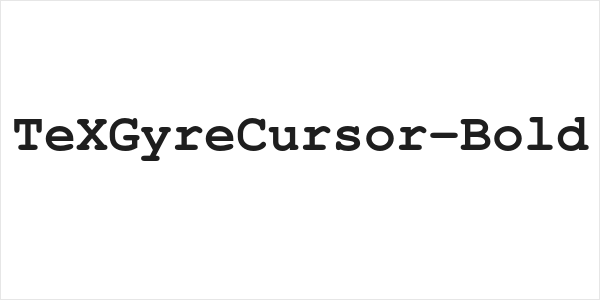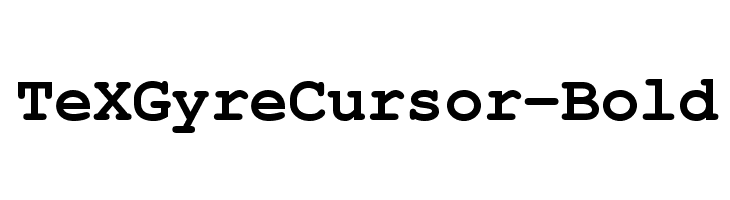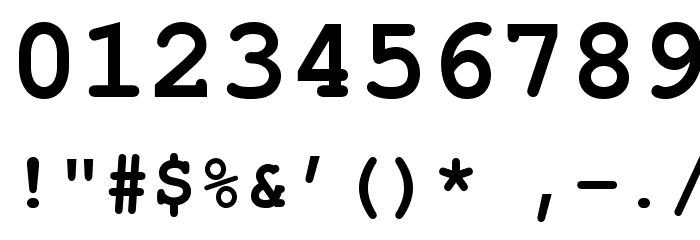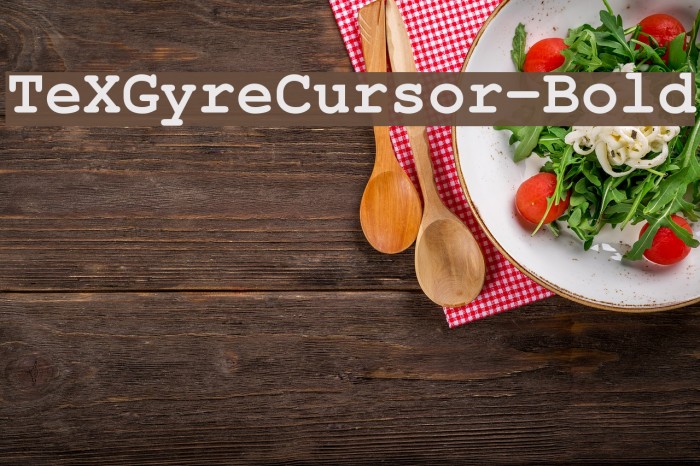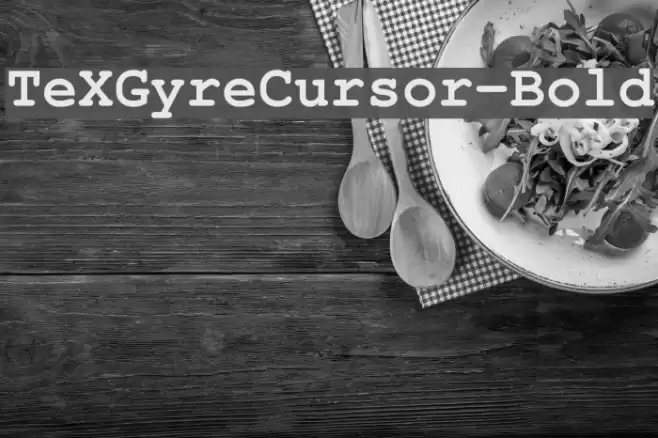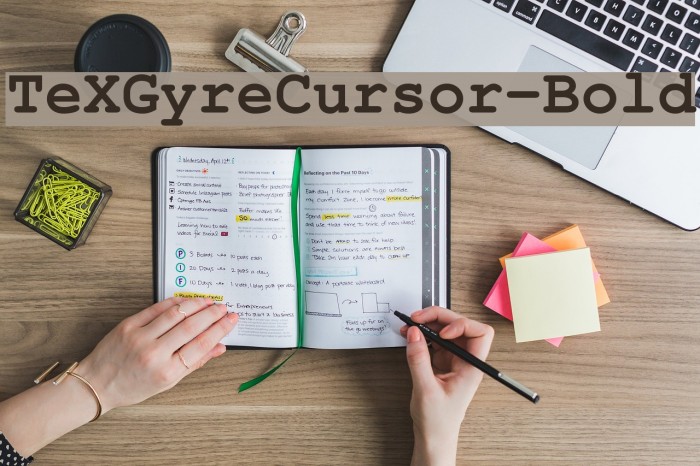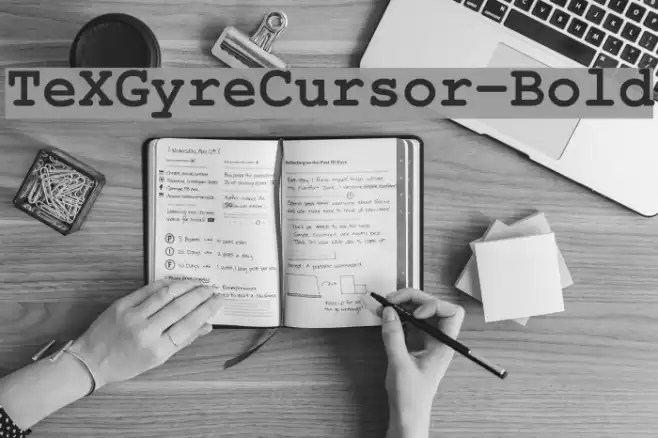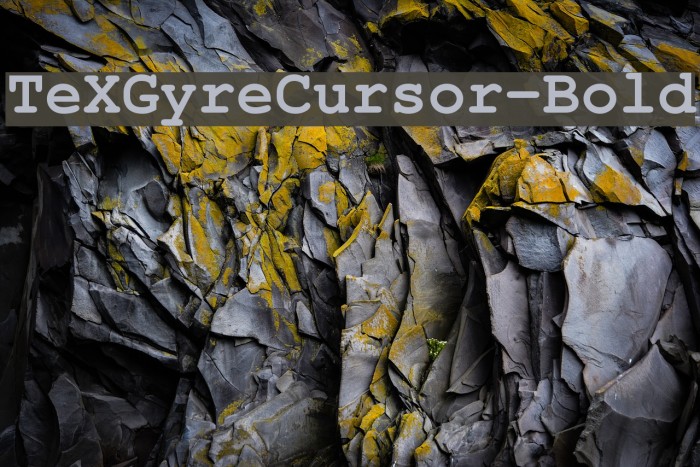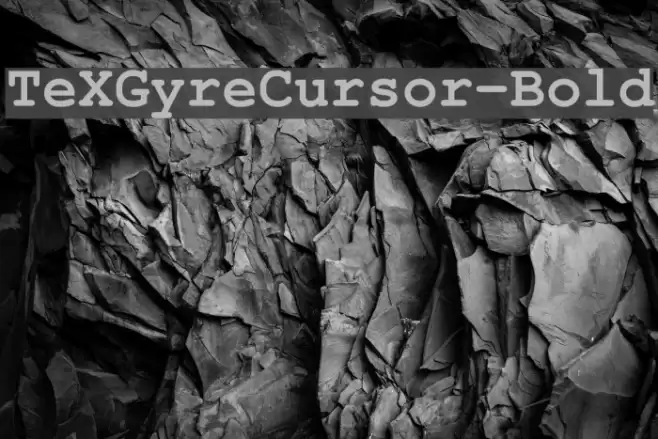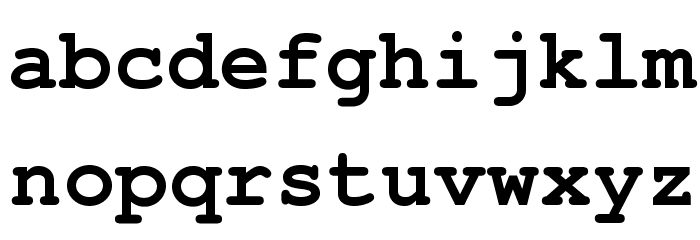
TeXGyreCursor-Bold Font
✎ Typewriter
| カテゴリ | Typewriter |
| 用途 | Coding, Technical documentation, Retro designs |
| おすすめプロジェクト | Ideal for coding environments, technical documentation, retro-themed designs, and any project requiring a typewriter aesthetic. |